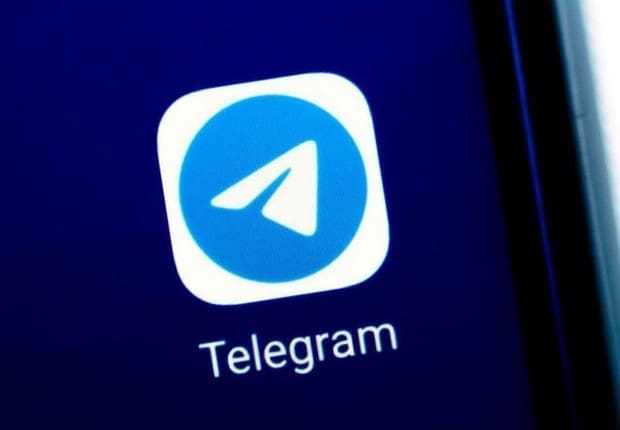
Ubah Font Telegram Kamu Agar Lebih Estetik
Telegram menjadi salah satu aplikasi yang kian populer di masyarakat selain whatsapp. Sebab, Aplikasi ini menawarkan berbagai fitur untuk menyesuaikan pengalaman pengguna, termasuk kemampuan untuk mengubah font.
Jika gaya tulisan aplikasi tersebut dapat kamu ubah, maka kamu dapat membuat tampilan obrolan menjadi lebih menarik dan sesuai dengan preferensi pribadimu. Pas banget nih, artikel ini akan memberikan kamu tips mengubah tampilan gaya font atau penulisan di telegram kamu. Simak informasinya berikut ini ya!
Ubah Font Telegram Kamu Agar Lebih Estetik
Terdapat beberapa cara yang dapat kamu lakukan untuk mengubah jenis dan tampilan font telegram mu.
Mengubah Font dari Pengaturan Obrolan
• Buka Aplikasi Telegram
• Buka aplikasi Telegram di perangkat yang kamu gunakan baik smartphone ataupun Desktop.
• Masuk ke Pengaturan Obrolan
• Klik ikon tiga garis di sudut kiri atas layar dan pilih “Pengaturan.”
• Pilih Pengaturan Obrolan
• Scroll ke bawah dan klik opsi”Pengaturan Obrolan.”
• Ubah Font
• Pada opsi “Font,” kamu dapat memilih dari daftar font yang tersedia, seperti Default, Serif, dan Monospace.
• Cara ini terbilang biasa, namun ada juga cara yang bisa kamu lakukan sehingga tampilan berubah secara otomatis.
Mengubah Font Menggunakan Bot Telegram
Selain mengubah font secara manual, Telegram juga memiliki beberapa bot yang memungkinkan kamu mengubah font dengan cepat dan mudah. Berikut adalah beberapa bot populer:
1. @italicbot: Bot ini dapat mengubah teks menjadi miring.
2. @strikethroughbot: Bot ini dapat menambahkan coretan ke teks.
3. @boldbot: Bot ini dapat mengubah teks menjadi tebal.
4. @underlinebot: Bot ini dapat menambahkan garis bawah ke teks.
Agar dapat menggunakan bot ini, kamu perlu menambahkan nama bot ke teks kamu dan ikuti dengan teks yang ingin kamu ubah. Contohnya, untuk mengubah teks menjadi tebal, tambahkan “@bold” Di awal teks.
Sebagai informasi tambahan bahwa Kamu dapat menggunakan beberapa bot secara bersamaan untuk menghasilkan efek yang unik. Cobalah untuk berkreasi dengan font dan efek yang berbeda untuk menemukan kombinasi yang paling sesuai dengan keinginanmu.
Pastikan kamu menggunakan font yang mudah dibaca, terlebih untuk sebuah informasi penting. Gunakan berbagai kemudahan telegram dalam mengirim pesan agar tercipta pengalaman mengobrol lebih menyenangkan.